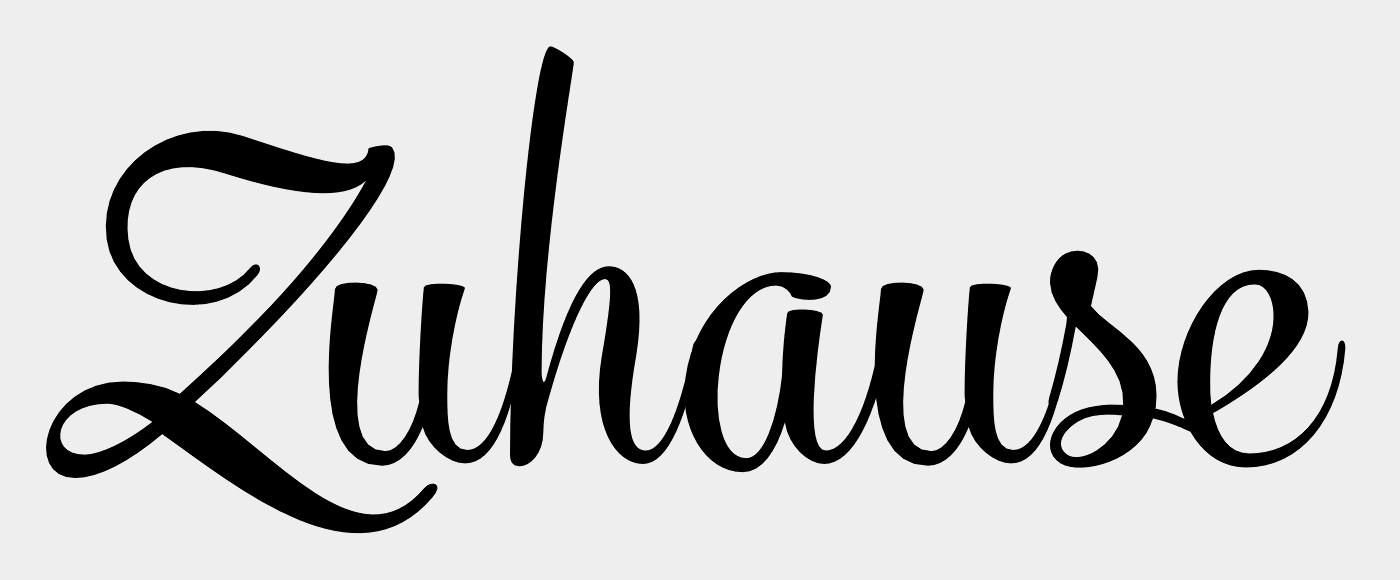
Kenn mich jemand?
Kennt von euch vielleicht jemand diese Schriftart?
Die gefällt mir sehr gut, nur finde ich diese einfach nicht.
mit diversen OpenType Contextual Alternates.
Keine Ahnung, ich kenn den Fragesteller und seine Erfahrung mit Schriften nicht ;-)
Jedoch hat catfonts recht, so richtig weiß ich mit der Aussage nichts anzufangen :-)
Das bedeutet, dass die Schrift für einige Buchstaben nicht nur eine sondern mehrere Formen kennt, die über sog. OpenType-Features entweder automatisch oder manuell angesprochen werden können. Das ist besonders bei handschrriftartigen Schriften gut, weil dann nicht alle Buchstaben gleich aussehen – wie bei einer echten Handschrift – und bspw. komplexere Buchstabenverbinungen möglich werden.